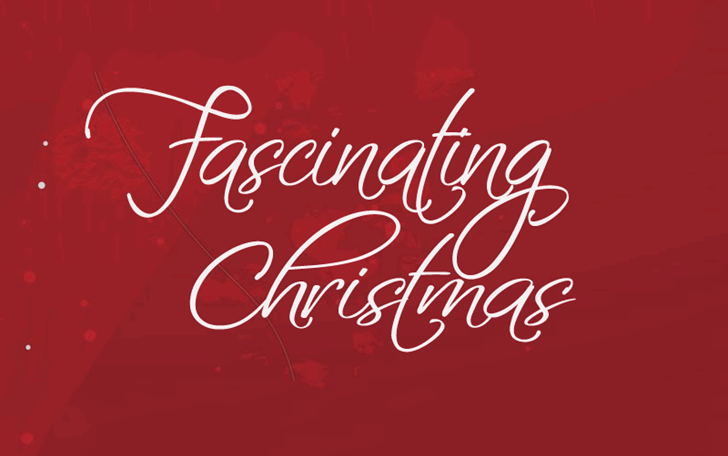
Fascinating Christmas Font
Aqui está uma descrição envolvente e natural para a página de download da fonte “Fascinating Christmas Font”, adaptada ao tom solicitado: Para as pessoas que adoram um Natal com estilo, aqui está a oportunidade perfeita! Se você quer incorporar o clima natalino em suas produções pessoais sem pagar nada extra, é seu momento. A fonte “Fascinating Christmas” foi criada por Cat Butcher e não só combina harmonicamente com as letras de Natal tradicionais, mas adiciona um toque único e artístico que certamente deixará seus trabalhos ainda mais interessantes. Esta fonte é perfeita para aqueles que são amantes da arte e do design. Ela oferece uma experiência única em termos de estilo e personalização, tornando-a uma escolha atraente tanto para designer gráficos quanto para quem usa suas habilidades em projetos pessoais. Em um momento tão especial como o Natal, ter uma fonte que reflete esse espírito pode fazer toda a diferença. A fonte “Fascinating Christmas” é criada pelo design do gênio Cat Butcher, e embora seja gratuita para uso pessoal, ela não deve ser usada em qualquer conteúdo comercial ou com conteúdo sexual. A designer toma medidas cautelosas para proteger seu trabalho original. Se você deseja obter o conjunto completo da fonte, simplesmente entre em contato através do email:  e Cat Butcher certamente atenderá suas necessidades. Agora, se você está procurando por um presente de Natal perfeito para seus projetos gráficos ou pessoais, esta é a escolha ideal. Embarque nesse espírito natalino com “Fascinating Christmas Font” e deixe que sua arte brilhe em estilo durante o mês mais especial do ano.
Designer: Cat Butcher